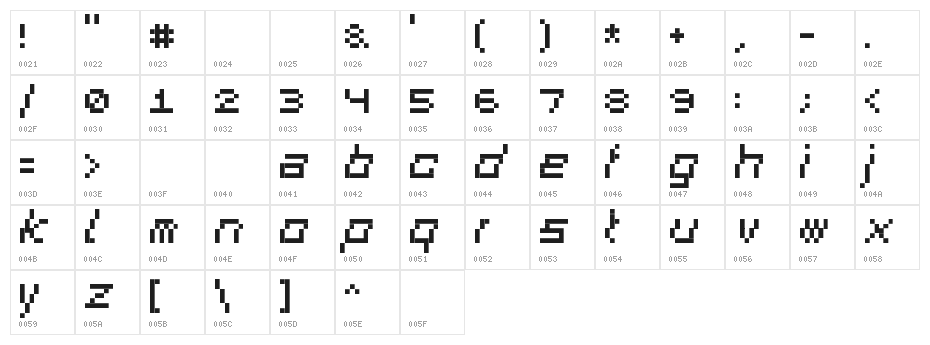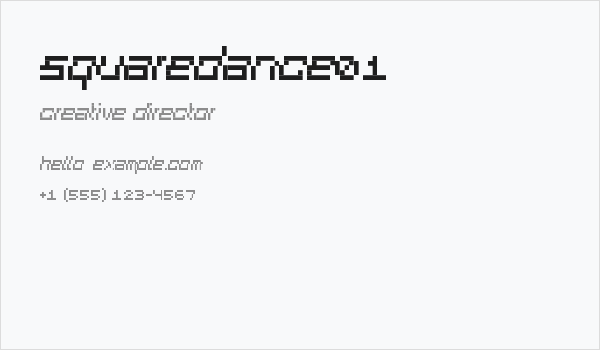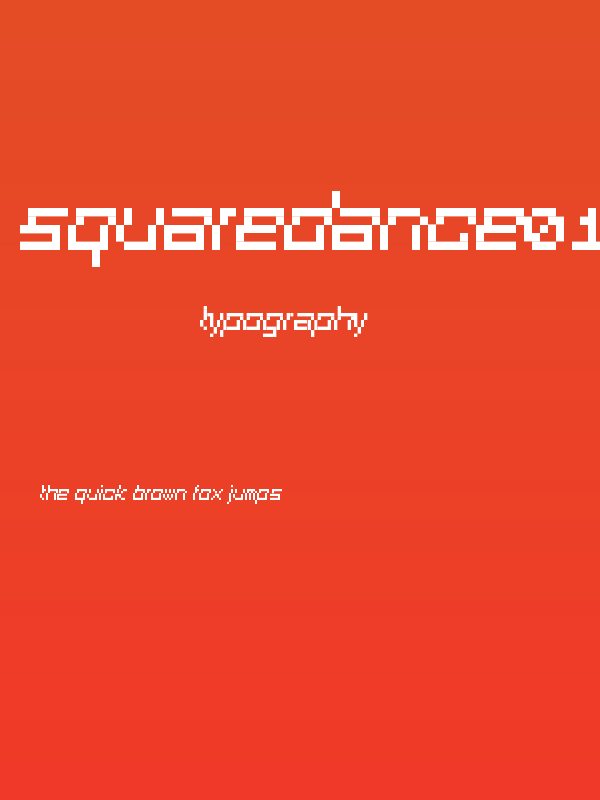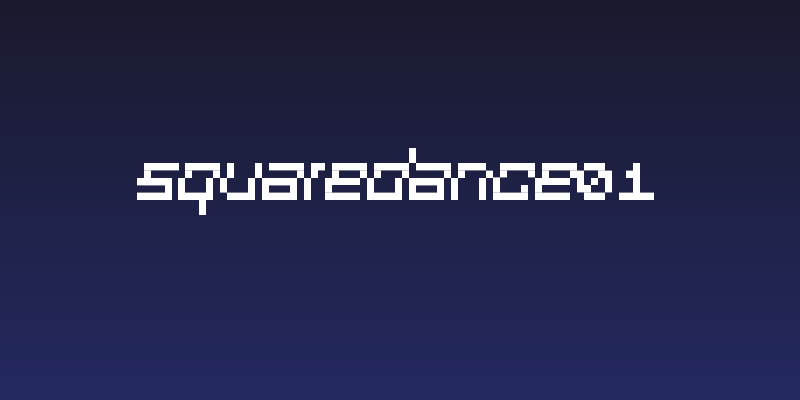
SquareDance01 Font
| Cas d'utilisation | Logos, Headlines, Digital Art |
| Projets proposés | Ideal for retro video game graphics, digital art projects, tech-themed posters, and nostalgic branding. |